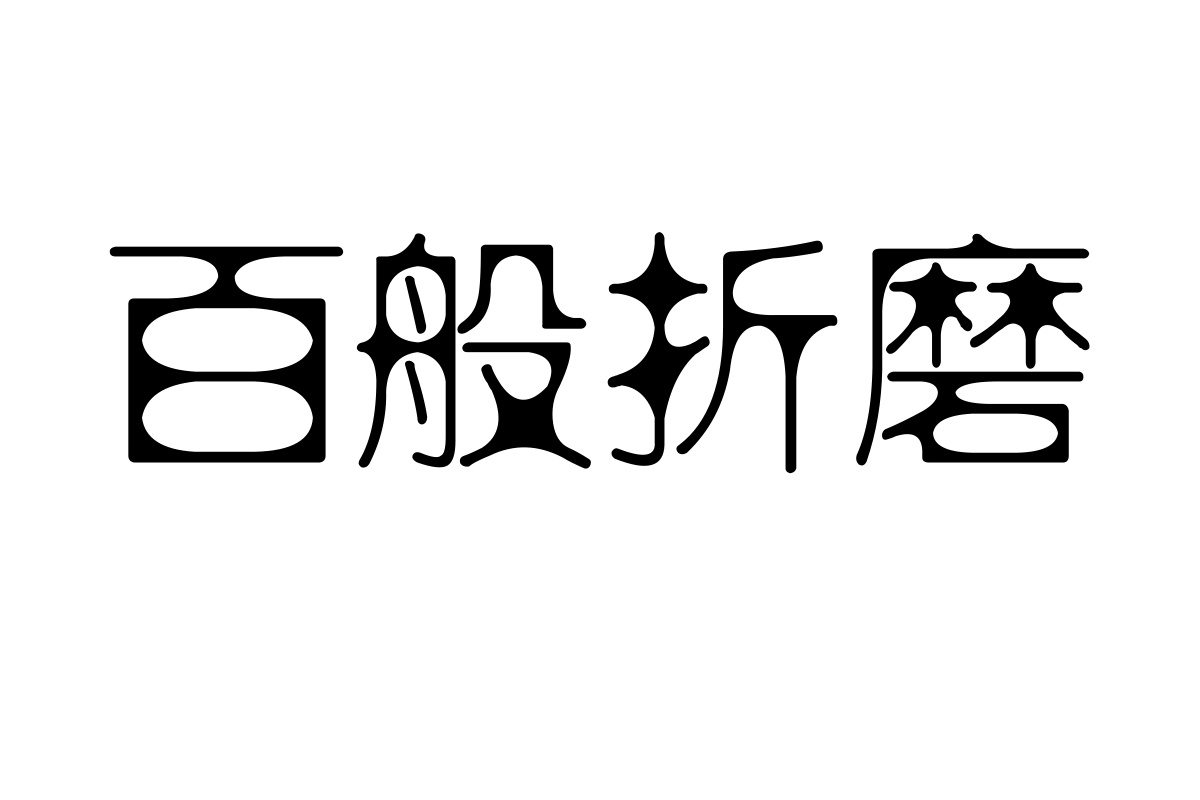
迷你简细珊瑚字体是一款专为中文设计,具有简洁和现代感的字体。它由多个字符组成,每个字符都经过精心设计,以确保清晰可读。这款字体适合用于需要强调文字清晰度和易读性的场合,如广告、海报、网页等。
该字体的特点包括:
– 简洁的字形设计,易于识别和记忆。
– 每个字符都有独特的风格,使得整体看起来更加协调。
– 适用于多种应用场景,如广告、海报、网页等。
– 提供不同字重和行距的选择,以满足不同的设计需求。
总的来说,迷你简细珊瑚字体是一款非常适合中文设计的字体,无论是在商业还是个人项目中,都能为作品增添一份独特的魅力。